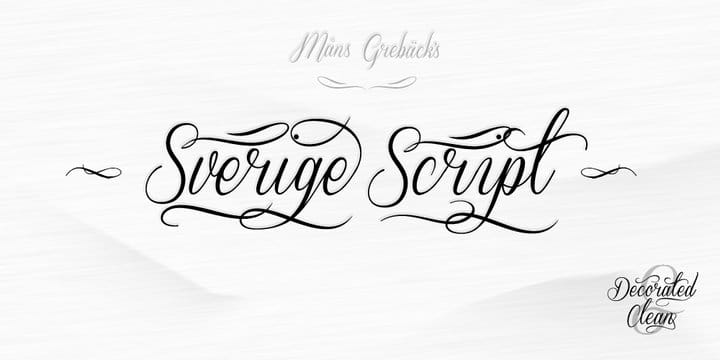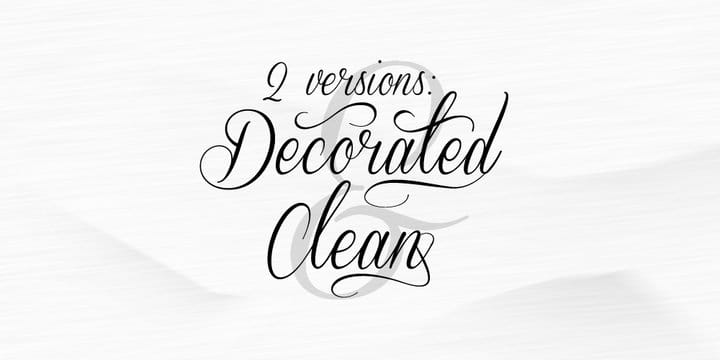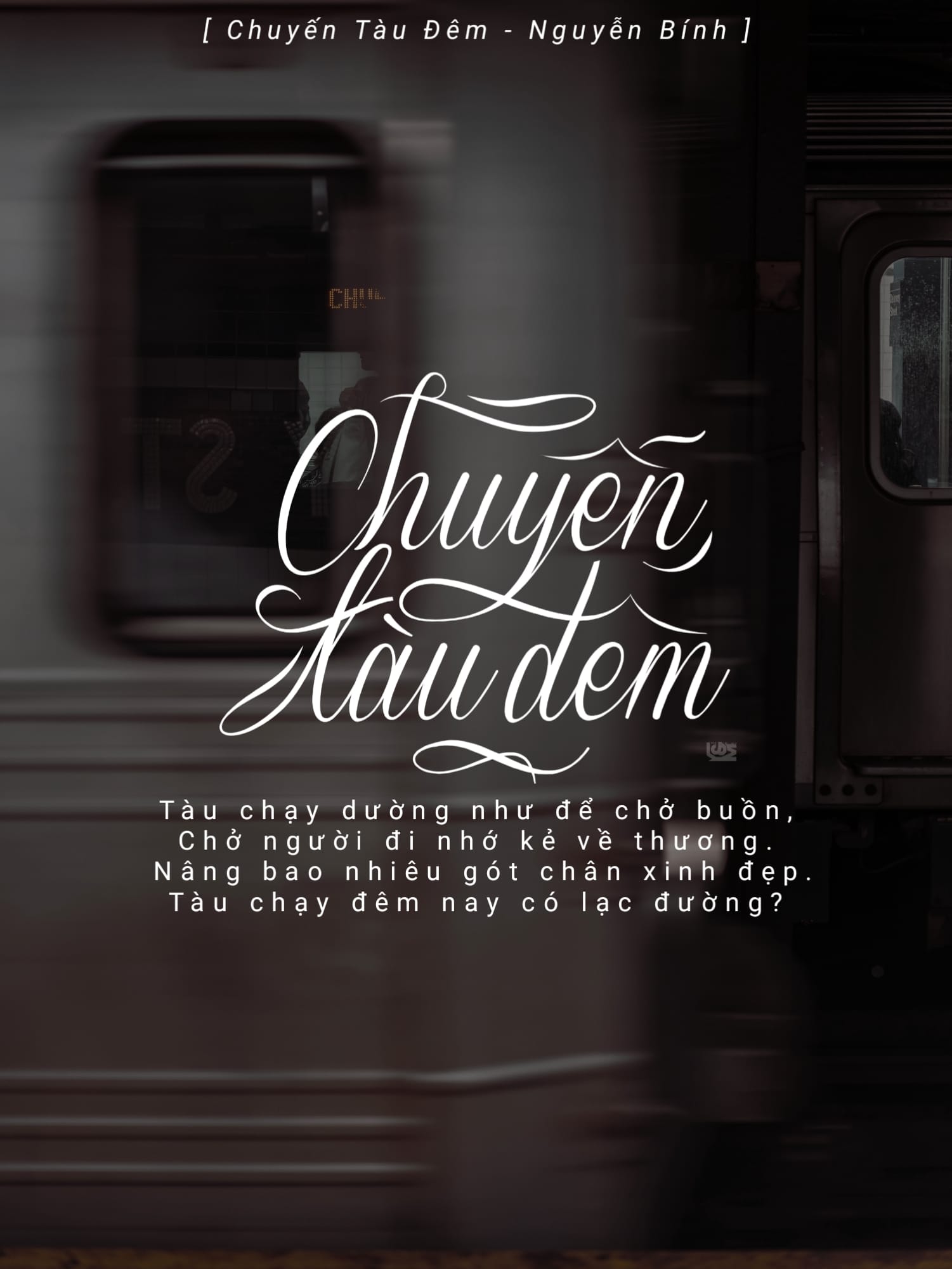
Font Sverige Script Việt Hóa là một font chữ khá ấn tượng và điệu đà phù hợp cho rất nhiều thiết kế của bạn như thiệp mời, bao bì, typo hay bất cứ thiết kế nào phù hợp với bạn. Lưu ý font chữ chỉ sử dụng mục đích cá nhân.
Bao gồm 2 font Việt Hóa: Sverige Script Decorated và Sverige Script